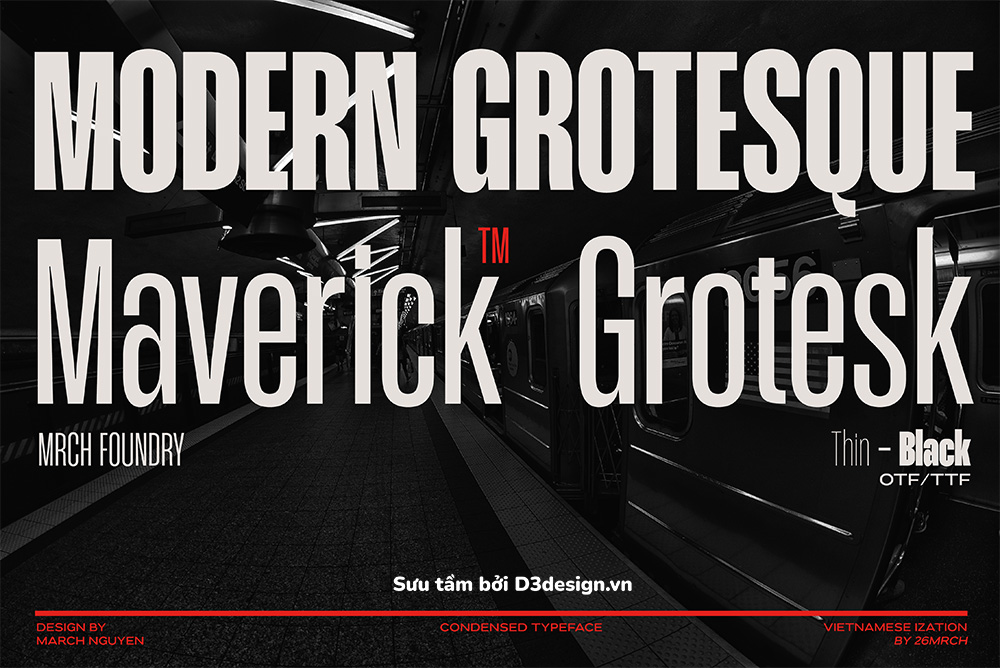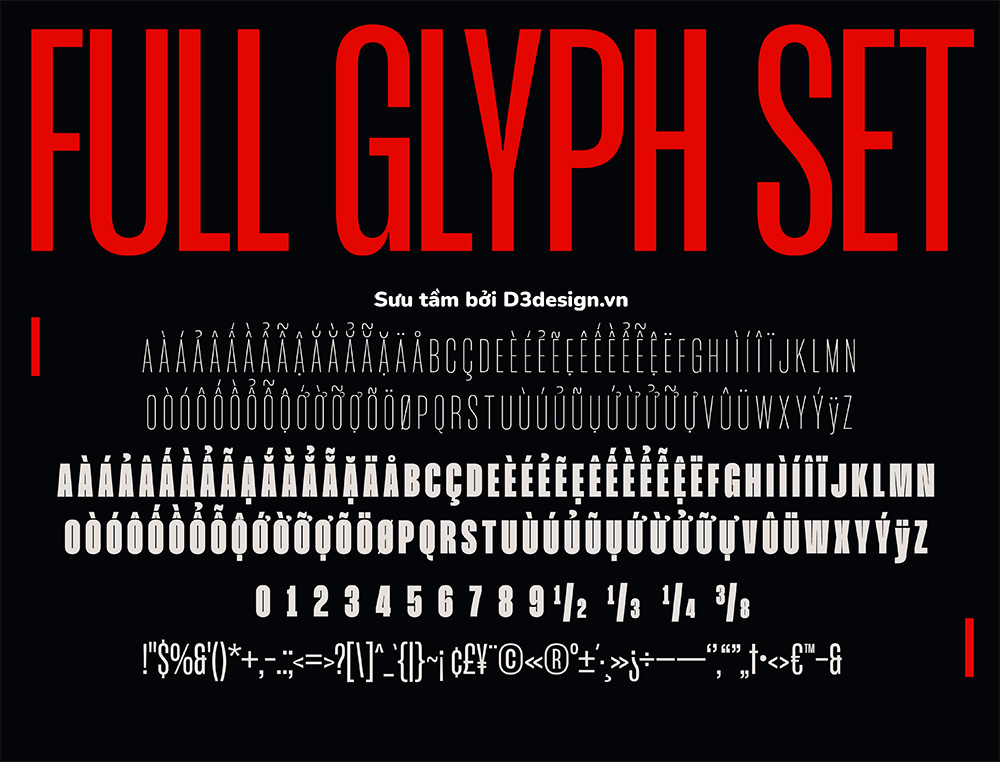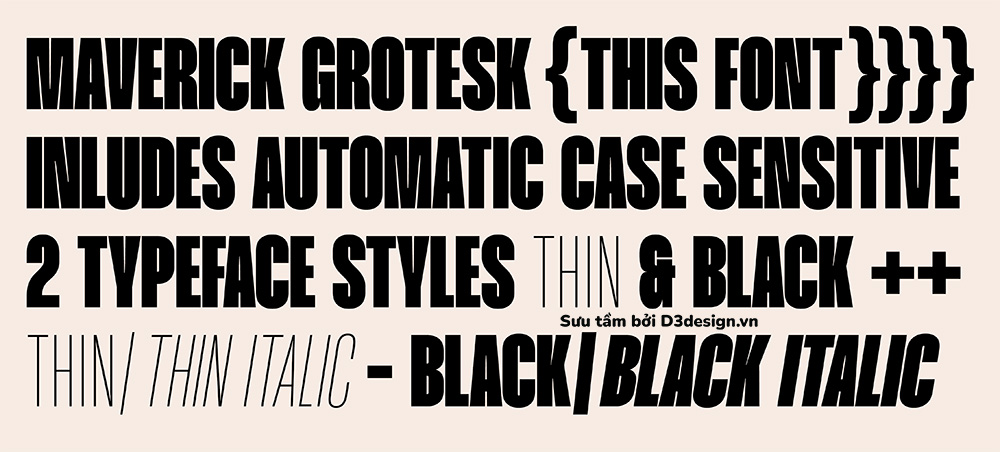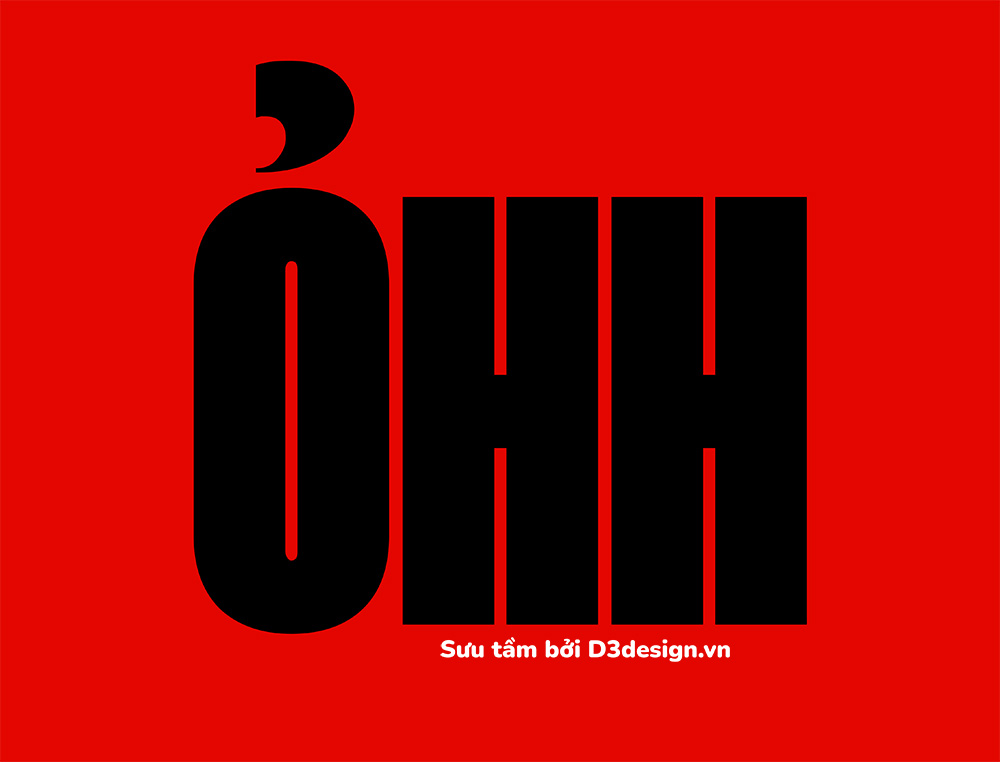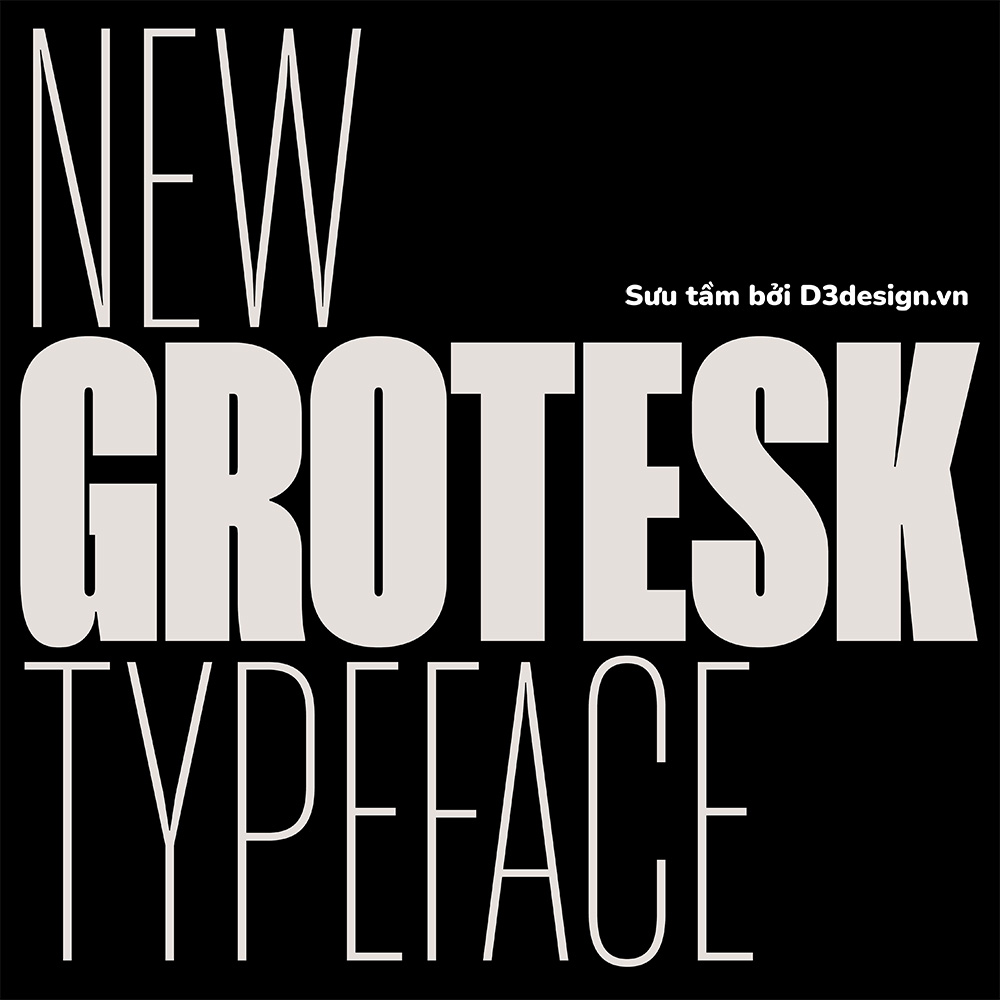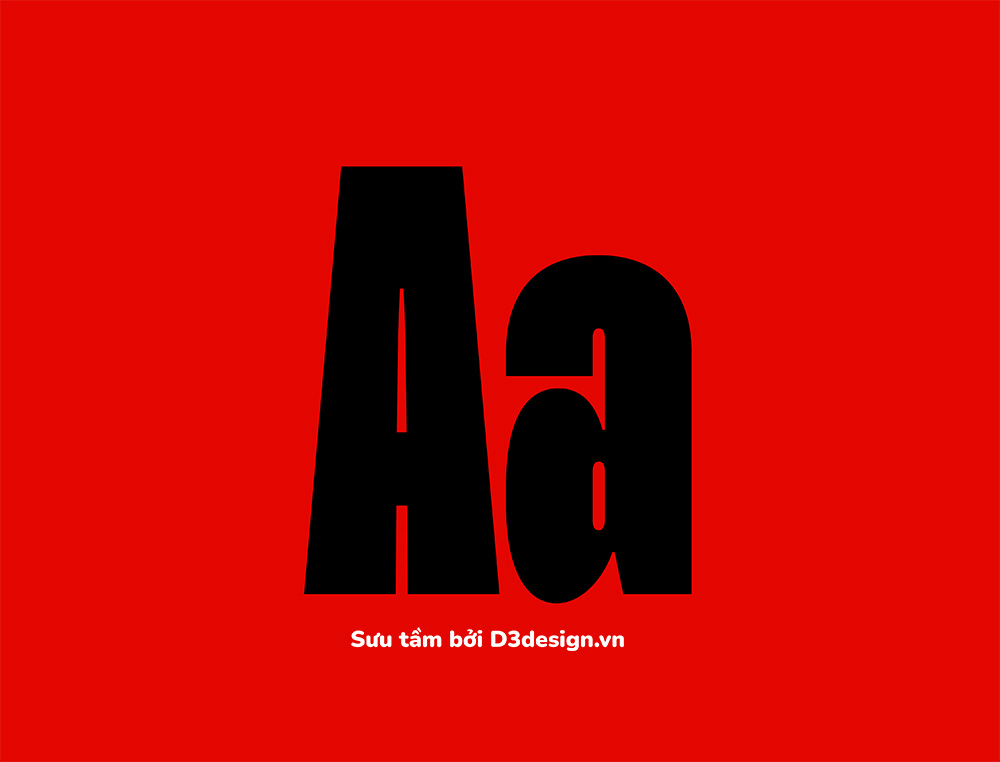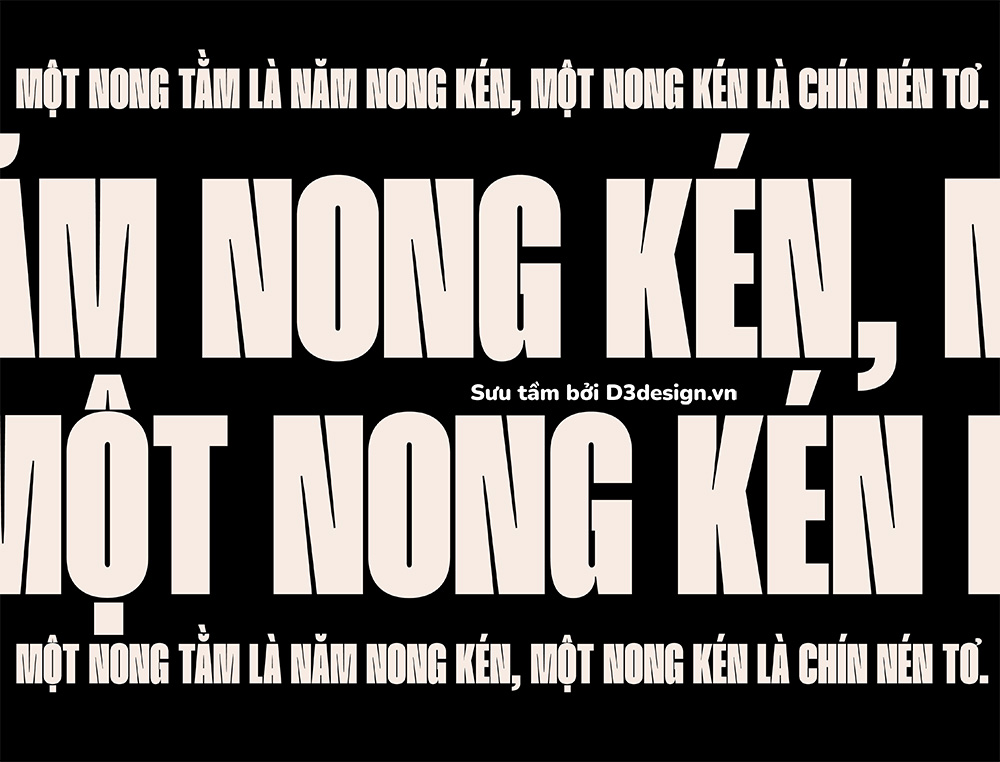
Font Việt Hóa - Maverick Grotesk Font Tiếng Việt Kiểu Chữ Condensed
Maverick Grotesk là phông chữ được thiết kế bởi 26MARCH. Là một kiểu chữ condensed được coi là phiên bản thu hẹp hơn của kiểu chữ tiêu chuẩn. Chiều rộng hẹp và ký tự cao làm cho nó trở thành một lựa chọn để lấp đầy những không gian chật hẹp hoặc nhiều dòng chữ.
Do tính chất cao, hẹp và các chữ cái có khoảng cách gần nhau hơn nên Maverick Grotesk được cho là khó đọc hơn phông chữ có kích thước thông thường. Tuy nhiên, đặc điểm độc đáo này có thể được tận dụng để tạo ấn tượng lâu dài với người đọc.
Với kiểu chữ này, bạn có thể làm được rất nhiều điều cho thiết kế đồ họa như gây ấn tượng với khán giả là nổi bật kiểu chữ cho thiết kế của bạn. Đó là lý do tại sao điều quan trọng là phải nhận ra giá trị và công dụng của nó.
Cho dù bạn đang làm việc trên đồ họa thông tin, bảng hiệu, thiết kế web, xây dựng thương hiệu, tạp chí hoặc bất kỳ thiết kế đồ họa nào, bạn đều có thể tìm thấy cách sử dụng condensed font.
Maverick Grotesk bao gồm 4 kiểu Thin, ThinItalic, Black và BlackItalic, font hỗ trợ đa ngôn ngữ, được miễn phí sử dụng cho mục đích cá nhân và thương mại.